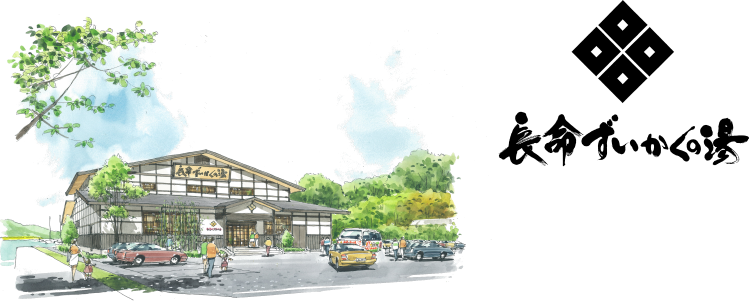
琵琶湖の夕日を望む地。
歴史と自然に抱かれた近江八幡 長命寺。滋賀県随一のラドン含有量を誇る健康長寿の天然温泉・サウナと近江の恵みを活かしたミシュラン2つ星のお食事が出来る、日帰り温泉です。
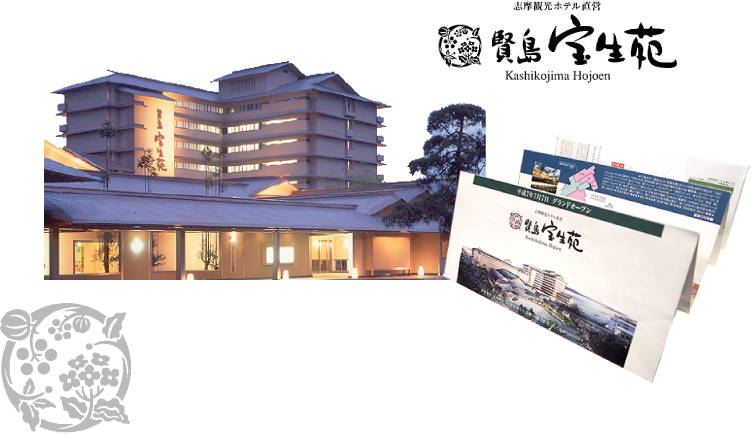
昭和天皇が行幸の砌、こよなく愛された賢島の地「宝生の鼻」。
賢島宝生苑という名前はその尊い場所に由来しています。
青い真珠の海、英虞湾を望む和風リゾートとして18 年前に揮毫させて頂きました。
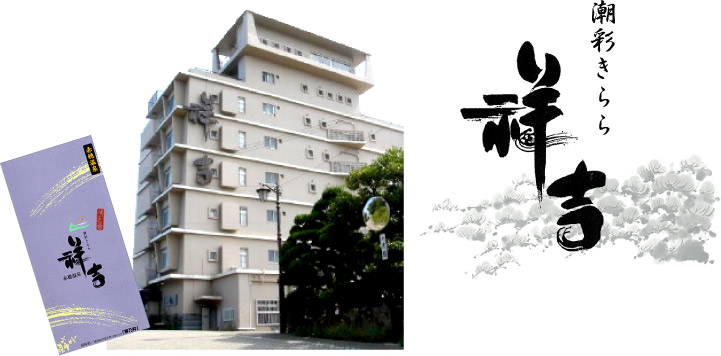
兵庫県赤穂温泉の旅館、潮彩きらら祥吉。
自ら体感した穏やかな瀬戸内の美しい海景色、
打ち寄せる波打ち際のイメージがポイントでした。
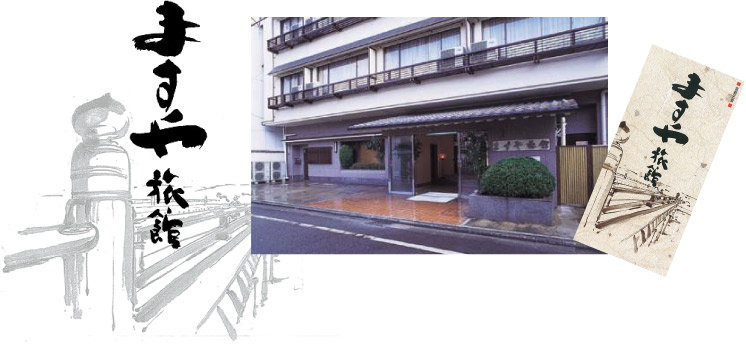
京都三条大橋鴨川畔に在するますや旅館。
京都の風情を伝え、旅のつかれを癒すくつろぎの宿として懐のあったかさを演出。
そんなイメージで作り上げました。